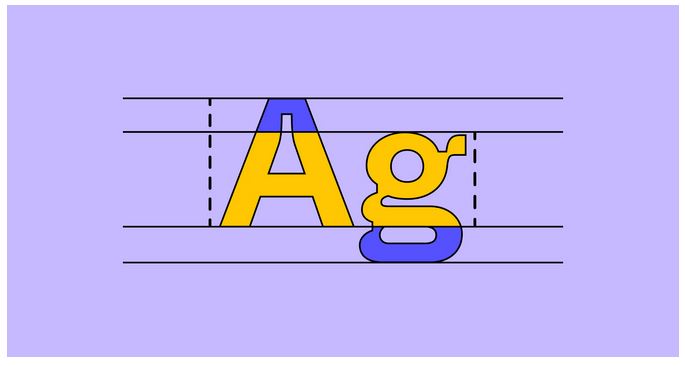
第一印象至关重要,这是每位品牌专业人士都深知的事实。如果内容不够清晰且缺乏吸引力,大多数用户会迅速离开网页。您的创意团队竭力以生动易懂的语言传递品牌信息。如今,他们正寄希望于您做出优秀的排版与设计决策,以提升可读性和品牌互动性。
什么是排版?
排版设计涉及创建或选择字体系统,以表达书面文字。这种创意艺术形式可通过视觉吸引人的字母和排版布局,传递品牌个性。精心设计的排版能提升沟通效果,确保文字易于阅读和理解。
为什么排版设计重要?
排版设计在打造优质网站、应用程序、邮件、电子书等数字内容中发挥关键作用。优秀的排版可以帮助您:
- 吸引用户:通过字体和排版元素在用户开始阅读前就吸引他们的注意力。
- 建立视觉层次:通过一致的字体大小、粗细、衬线与无衬线字体、字体搭配及字体组合,引导用户并提升可读性。
- 建立品牌识别:当排版元素被一致使用时,优秀的排版能帮助用户通过品牌内容中使用的字体和字体样式识别您的品牌。
- 支持内容目标。一致的字母间距、行长、大小写字母及其他排版元素提升可读性,而作为图形设计元素的字体则强化语气和含义。
排版简史
约翰内斯·古腾堡在15世纪通过发明第一台金属活字印刷机,引发了欧洲字体设计的革命。古腾堡使用旧式黑体书法字母(即哥特体)来排版手稿和宗教文本中的较长文本行。意大利的印刷商随后创造了一种更简单、更紧凑的字体——最初称为Antiqua,现在更广为人知的是Roman。欧洲印刷商随后推出了斜体字体,使每页能够排版更多的文字。
快进到18世纪末至19世纪初,第一款现代衬线字体问世。无衬线字体随后出现,并主导欧洲印刷界直至20世纪。此时,更简洁易读的字体如Times New Roman、Futura、Helvetica和Arial开始流行。如今,全球的平面设计师和网页设计师都可以访问庞大的字体库。
5种最受欢迎的字体类型
现代设计师通常从五种流行的字体类型中选择:衬线体、无衬线体、手写体、等宽体和展示体。每种字体都包含一个字体家族,涵盖该字体的各种风格。例如,Helvetica是一种字体,而Helvetica Light和Helvetica Regular是字体。
- 衬线字体:这种正式、传统的字体在字母的上下端有短线或笔画延伸。知名品牌如《纽约时报》、索尼和摩根大通选择衬线字体。示例包括 Times New Roman 和 Garamond。
- 无衬线字体:这种简洁现代的字体没有衬线字体中的装饰性笔画。它是年轻品牌和科技初创公司的热门选择(如 Target、Airbnb 和 Doordash)。无衬线字体示例包括 Helvetica、Arial 和 Calibri。
- 脚本字体:这种流畅的草书字体风格多样,从优雅的书法到活泼的手写体均有涵盖。不适合正文文本,脚本字体最适合用于引用、签名和短标题。示例包括Snell Roundhand、Pacifico和Scriptina。
- 等宽字体:这种复古的打字机风格字体采用固定宽度字母和间距,确保每个单词的字符占用相同宽度。等宽字体常用于源代码以提升可读性,同时在众多网站和图形设计中广泛应用。示例包括Courier、Bergen Mono和Source Code Pro。
- 展示字体:也称为装饰性字体,这种引人注目的字体可为标志、横幅和标题增添独特风格和创意。展示字体示例包括Clearview、Johnston和Skywalker。
排版的关键元素
通过调整一个或多个排版元素,您可以微调文字、文本行或产品的视觉效果、可读性和氛围。
对齐
为了实现平衡并帮助用户轻松浏览页面,需对设计元素(如 logo、图片、标题和正文文本)进行对齐。确保各设计元素间距均匀,并一致使用边距和填充。根据项目需求,可将文本左对齐、右对齐、全对齐或居中对齐。例如,设计师可能将标题或短引用居中对齐,但将长篇内容左对齐。
颜色
选择与品牌一致且清晰传达信息色彩方案。调整文字透明度,并使用互补色以确保可读性和可访问性。可使用色彩轮生成器创建平衡的色彩方案。专业提示:参阅《网络内容可访问性指南》以获取理想对比度比例。较鲜艳的色彩更适合标题和副标题,而中性色彩则适合大段文字。
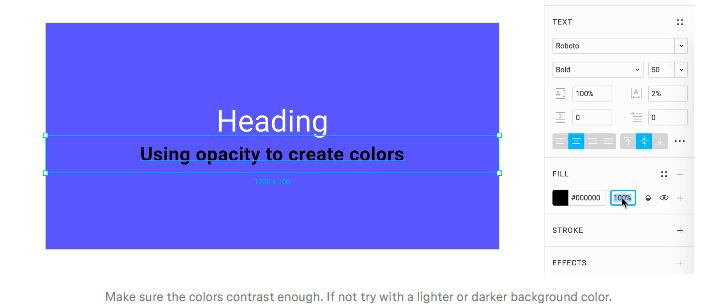
层次
在排版中建立层次结构有助于突出重点信息,使其易于快速浏览和理解。标题应比副标题更大,副标题又比正文文字更大。例如,网站正文文字通常为16px,H1标题设置为48px。通过调整空白空间、文字对齐方式、颜色和字体类型,进一步强化视觉层次结构。
字距调整
调整字母之间的间距,使距离看起来一致。适当的字距调整可以提升文本的视觉吸引力,同时改善可读性。
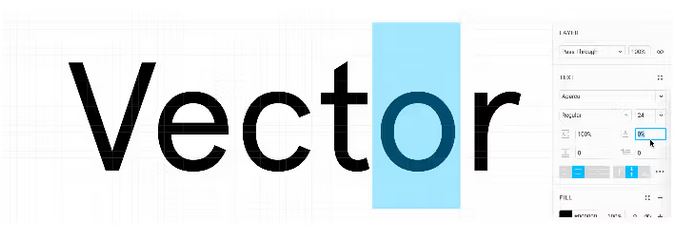
行高
行高指的是两行文本之间基线之间的距离。一般来说,行高设置为字体大小的1.125倍至1.200倍(即112.5%至120.0%)能提升可读性。不过,每种字体都需要精细调整,包括行间距的精心设置。
字距
通过字符间距(即字符间距)可以提升可读性,它指的是单词或文本行中字母之间的整体间距。增加字符间距可增加间距,减少字符间距可缩小间距。全部大写显示的单词或短语有时在增加字符间距后更易阅读。
如何选择合适的字体
选择字体的过程可分解为以下关键步骤:
- 考虑项目范围、需求和目标。向团队提出关键内容问题:我们通过何种方式传递内容(应用程序、网站、电子邮件或印刷材料)?我们的受众是谁,他们的需求是什么?竞争对手使用哪些字体和字体样式?请记住,某些字体更适合标题,而其他字体则更适合菜单文本。部分字体拥有庞大的字体家族,支持国际脚本、字符和特殊符号。
- 创建 mood board 以基于用户研究和竞争分析确定视觉风格。可使用 FigJam 的 mood board 模板 开始。专业提示:参考类似解决方案可帮助识别有用模式和规范。
- 探索字体选项在您的计算机上或在网站如 Google Fonts。寻找一种字体,其视觉元素与您希望产品或品牌传达的形象相呼应。例如,如果您的品牌基调是专业而非轻松,应选择一种严肃的字体,尽量减少装饰元素。以下 Figma 设计示例中,哪个看起来更专业?如果您选择了左侧的模块,您就走在了正确的轨道上。该模块使用了 Roboto,一种干净、易于阅读的无衬线字体。右侧的模块使用了 Almendra,一种基于书法风格的字体,常用于儿童书籍。
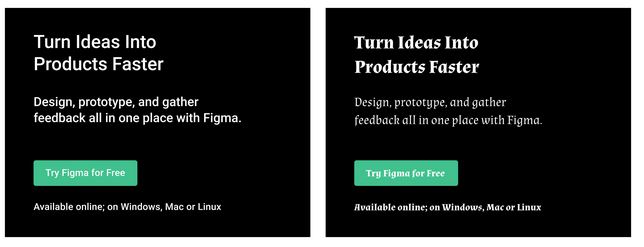
- 选择符合品牌风格且引人注目的字体以支持项目目标。考虑字母的整体结构(例如:x高度、大写高度、字间距、上伸部分和下伸部分)、可缩放性、可读性、个性特征及装饰元素。这些要素共同影响字体的整体视觉效果。
- 使用真实且相关的文本内容测试字体。这是选择能吸引用户字体的最佳方式。尝试将字体应用于不同尺寸,确保其在大小文本中均能良好呈现。
- 在字体上测试品牌颜色。首先,将黑色文字放置在白色背景上,白色文字放置在黑色背景上。然后将品牌主色应用于文字,观察字体在白色和黑色背景上的效果。反转颜色,查看白色和黑色文字在品牌主色背景上的效果。
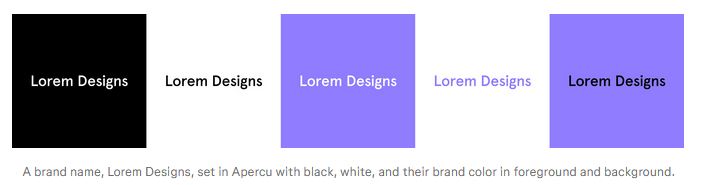
字重与字体样式
以字体为例,Julieta Ulanovsky 和其工作室设计的 Montserrat 字体包含多种字重和样式,如常规、粗体、斜体、细体、黑体等,每种都有对应的字体文件。字体文件用于安装和使用特定字重及文本样式的字符集。具有多种字重的字体包含每个字重的字体文件,这些字体文件共同构成一个字体家族。
蒙特塞拉特字体家族包含18种字体:超细、超细斜体、超轻、超轻斜体、轻、轻斜体、常规、常规斜体、中、中斜体、半粗、半粗斜体、粗、粗斜体、超粗、超粗斜体、黑体和黑体斜体。
字重指字母笔画的粗细程度。一种字体可以从极细到超黑,中间包含多种字重,而有些字体可能仅有一种字重。这些字重还对应数字编号,这在编程或与开发者协作时非常有用。字重通常对应于100到900的数值,间隔为100:常规400,中等500,半粗600,粗体700,等等。
字体样式是指对字符或字母大小的调整,例如斜体和全大写。有些字体没有样式选项,有时只提供常规字重。
字母大小写(也简称为“大小写”)是指区分小写字母(如小写字母)和大写字母(如大写字母或首字母大写)。大多数字体集包含两种大小写字母,而某些字体(如 Bangers)仅使用大写字母。仅使用大写字母或仅使用小写字母的字体则较为罕见。
在英语中,不同大小写样式根据具体情境使用:
- 标题大小写(Title Case)是一种混合大小写样式,其中句子中的所有单词首字母大写,但冠词、短介词和连词除外。这些例外情况具有一定主观性。
- 句子大小写(Sentence Case)是我们日常看到的文本书写方式,包括本句在内。
- 全大写(ALL CAPS)是指所有文字均使用大写字母,常用于标题、标志文字、按钮文字或其他类型标签。应将其用于强调,而非长篇文本,因缺乏上升笔画和下降笔画可能导致大段文字难以阅读。全大写在线上环境中常被用于表示大声喊叫,因此应避免在聊天或对话界面中使用。
- 小写大写与大写字母形式相似,但高度与字体的 x 高度相同。小写大写用于区分正文文本和标题文本,然而,许多字体并不提供此选项。
- 全小写文本是一种风格选择,用于某些产品和标志以实现美学效果。
字号
设置和更改字体大小是一个困难的决策。这将取决于文本出现的媒介,如纸张、手机或广告牌,并可能根据观众的设备或设计响应性而变化。
确定字体选择的层次结构至关重要,字体大小是强调元素之一。
在网页开发中,需定义一些关键字体大小,如标题、副标题、正文文本、菜单和页脚文本等。许多设计师从标题大小(即H1)开始,但从正文文本大小开始可能更具实用性,因为前端开发人员通常会以此为基础进行实现。当开发人员使用基于缩放的测量单位“em”时,正文文本大小为1em,其他所有文本大小均为其倍数或分数。
例如,网页中常见的正文文本大小为16px。H1可以设置为3em,即正文文本大小的3倍,即48px。由于网页设计需适配多种屏幕尺寸,您创建的布局可能需要根据客户设备调整字体大小。开发者可让正文文本大小随客户浏览器尺寸变化,其他文本将相应缩放。
细节
排版设计中很多细节和微妙之处。
例如,在布局文本时需关注“rag”现象。“rag“是指左对齐或右对齐文本的不规则边缘。可以通过调整文本框宽度或更改整个文本的字母间距来控制。
当一个或两个单词出现在段落末尾时,通常称为”孤行“(widow)。若出现在下一列开头,则称为”孤行”(orphan)。
然而,正如 May-Li Khoe 所指出的:
将一行文字中单独出现的单词称为“寡妇”或“孤儿”有点令人沮丧,尤其是因为我本人就是个孤儿。我更喜欢称它为“悬挂词”。
请将它们称为“悬挂元素”。
在调整文本框以避免悬挂元素时,行长也会相应调整。对于英文正文文本,将行长限制在约40至60个字符(包括空格和标点符号)是确保可访问性和可读性的理想设置。若行长需超过60个字符,请增加行高以提升可读性。
让文档或界面看起来设计良好的最简单方法之一是确保对象在空间中的位置一致。
假设你的应用界面有一个标题,它距离屏幕顶部100像素。你希望所有其他具有类似标题的应用界面都将这些标题放置在相同位置。
指南和测量工具是你的得力助手——只需在Figma的标尺上点击并拖动即可创建指南,当选中对象时按住Alt键即可查看与周围对象的距离。
考虑网站、海报、应用界面、信息图等布局中左侧(或左垂直边距)包含徽标、图片、标题和正文文本的区域。将这些元素相互对齐,不仅能让视线更顺畅地沿页面下移,还能使内容布局显得经过精心设计且富有目的性。
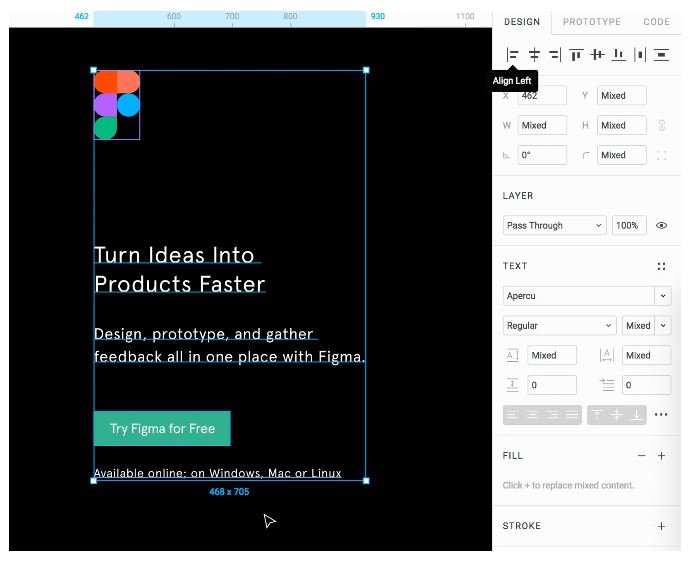
齐是块或文本行特有的对齐概念。
- 左对齐是指每行文本的开头在左边距处具有相同的 x 值。这也被称为左对齐,会在右侧产生不齐的文本。
- 右对齐是指每行文本的结尾与右边距齐平。这也被称为右对齐,会在左侧产生不齐的文本。
- 完全对齐是指文本行左右两端均与文本框两侧对齐。通过调整字母间距和单词间距,使每行文本宽度一致。完全对齐时不存在空行。
- 居中对齐是指文本未进行任何对齐操作。